Boowie
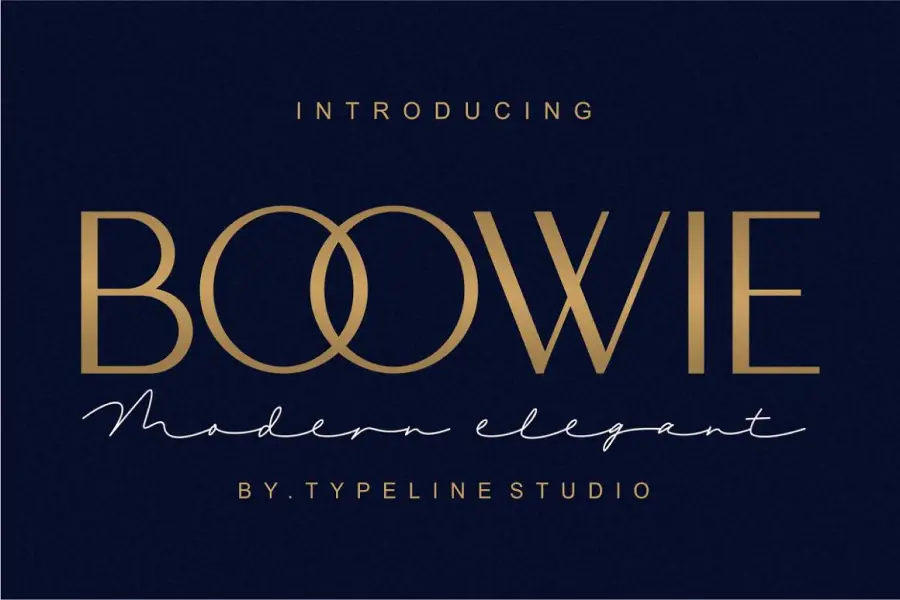
Boowie este un font minimalist care vine atât în versiuni obișnuite, cât și în versiuni italice. Cu liniile sale curate și estetica modernă se întâlnește cu vintage, este perfectă pentru a adăuga o notă de sofisticare oricărui proiect. Indiferent dacă proiectați un logo, materiale de imprimare sau chiar textul corpului, Boowie este o alegere versatilă care vă va ajuta munca să iasă în evidență.
Una dintre caracteristicile remarcabile ale lui Boowie este simplitatea sa. Lipsa detaliilor străine permite formelor și liniilor de bază ale literelor să strălucească cu adevărat. Acest lucru îl face o alegere excelentă pentru modelele care trebuie să fie atât atrăgătoare, cât și ușor de citit. În plus, versiunile obișnuite și italice pot fi combinate într-o varietate de moduri pentru a crea efecte și stări diferite.
Un alt aspect grozav al lui Boowie este flexibilitatea sa. Funcționează bine într-o gamă largă de setări, de la comunicări formale de afaceri până la eforturi mai creative, cum ar fi postere sau invitații. De asemenea, fontul se scalează bine, așa că îl puteți utiliza la diferite dimensiuni, fără a sacrifica calitatea sau lizibilitatea.
Froyas
Froyas este un font modern sans serif care poate adăuga o notă unică textului tău. Acest font a fost realizat cu mare grijă, iar fiecare literă iese în evidență în felul său.
Froyas este un font curat și minimalist, care funcționează bine pentru diverse proiecte. Este perfect pentru a crea logo-uri elegante, titluri elegante sau modele simple, dar sofisticate. Cu liniile sale ascuțite și curbele netede, Froyas captează atenția, păstrând în același timp simplitatea.
Acest font vine într-o gamă de greutăți, ceea ce vă permite să îl utilizați atât pentru titluri, cât și pentru textul corpului. Puteți alege dintre stiluri ușoare, obișnuite, medii, îndrăznețe și negre, în funcție de nevoile dvs. de design. În plus, acceptă mai multe limbi, ceea ce îl face o alegere ideală pentru proiecte internaționale.
Clarisa
Clarisa este un font minimalist care poate fi un plus excelent pentru proiectul tău personal sau de afaceri. Cu designul său elegant și simplu, Clarisa va oferi lucrării tale un aspect modern și profesional.
Acest font are linii curate și margini ascuțite, făcându-l perfect pentru logo-uri, titluri și alte materiale de branding. Are o prezență îndrăzneață și încrezătoare, păstrând în același timp un sentiment de eleganță și sofisticare.